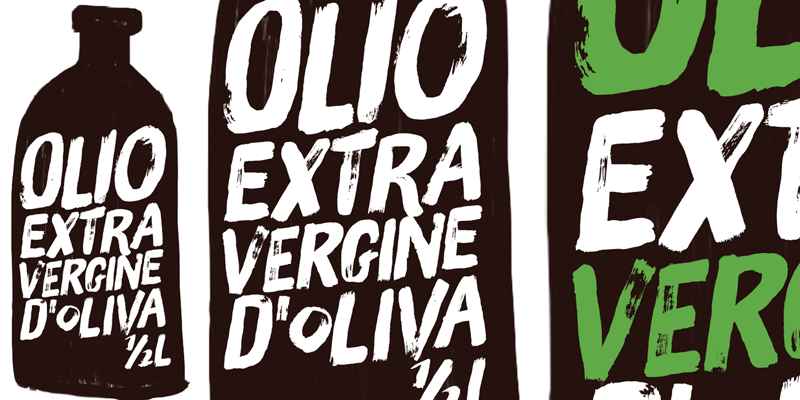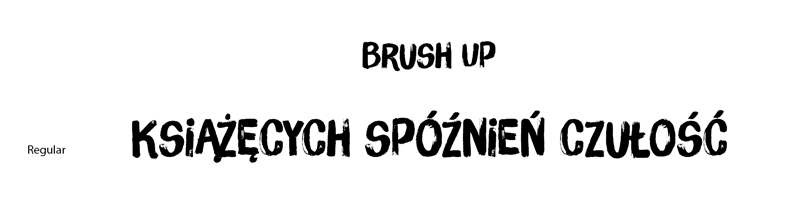
Font Brush Up
Do naszego studia trafił ozdobny font Brush Up zaprojektowany przez Ricardo Marcina i Erica Junga z Brazylii. Litery w foncie są namalowane ręcznie grubym pędzlem.